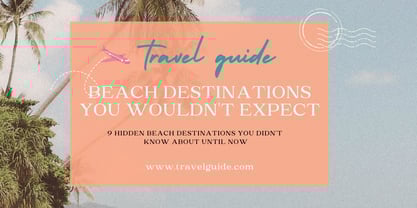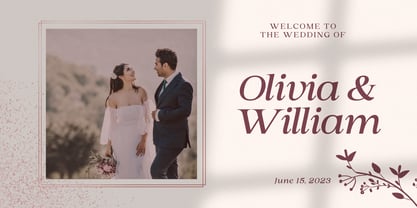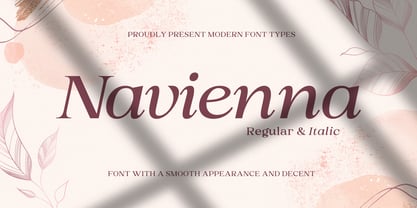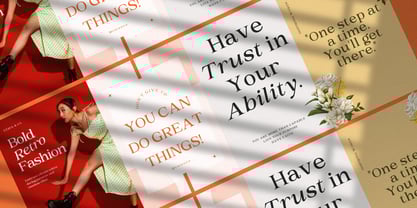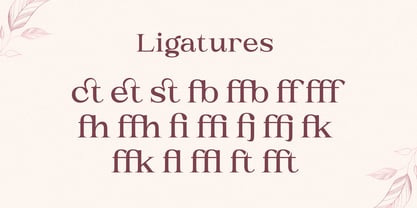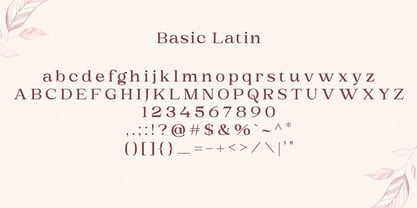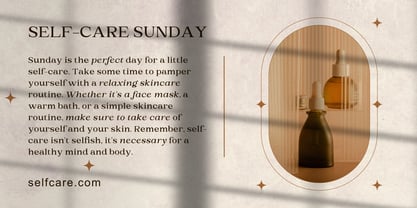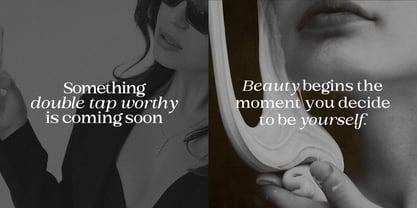
Navienna
La familia tipográfica Navienna fue diseñada por Candi Erwanto y publicada por Objectype. Navienna contiene 2 estilos y opciones de paquete familiar.
Elyssum is an elegant serif font that blends classical beauty with a modern touch, creating typography that is clean, professional, and highly readable.
Designed to meet the needs of various design projects, both print and digital, Elyssum combines balanced proportions with an ideal x-height, ensuring comfortable readability across different sizes and mediums. Its refined details and elegant touches exude a sense of luxury and high aesthetics.
Key Features:
• Versatility: Perfect for editorial designs, branding, invitations, and promotional materials.
• Clarity: Strikes a balance between traditional and modern for effective communication.
• Premium Features: Ligatures, kerning, multilingual support, and available in Regular and Italic styles.
Elyssum is the perfect choice for designers seeking to bring a professional, aesthetic, and timeless feel to their creations.